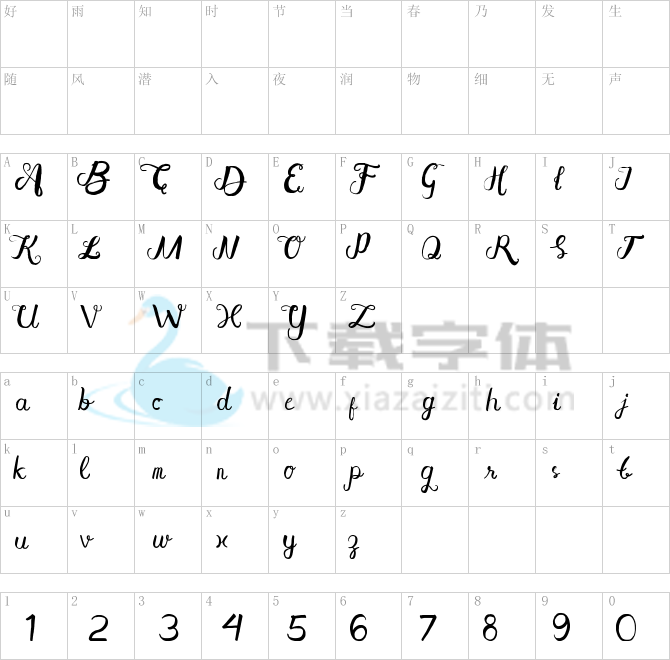
Aisy Khadijah.ttf字体下载,这款字体结构工整、笔画清晰,兼顾美观与易读性,适用于标题、正文、海报、包装、LOGO 等多种场景。字形优雅稳定,风格百搭耐看,适配日常排版与创意设计,让文字呈现更舒适、更具质感。Aisy Khadijah.ttf字体下载一笔一画,皆是细节,以均衡的比例、流畅的线条打造舒适视觉体验,字形端正大气,风格简约现代。无论是商业设计、品牌宣传还是日常排版,都能轻松驾驭,让文字更有格调与力量。Aisy Khadijah.ttf字体下载字体下载。